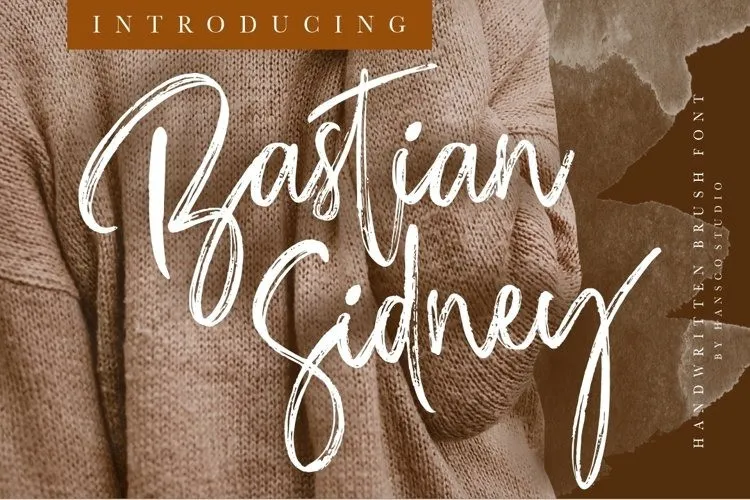
Bastian Sidney Font – Fonte Grátis
Bastian Sidney Font
Esta é uma fonte que foi raspada com uma caneta a mão para obter textura natural, mostrando as características de quem escreveu. Esta fonte é perfeita para criar logotipos, marcação de produtos, cartazes, posts nas redes sociais e muito mais! Ignite sua criatividade com esta fonte divertida. Se você está procurando por uma fonte que traz vida à sua ideia de projeto, a Bastian Sidney Font é exatamente o que você precisa. Experimente-a agora para começar a explorar todas as possibilidades desta font única e divertida.